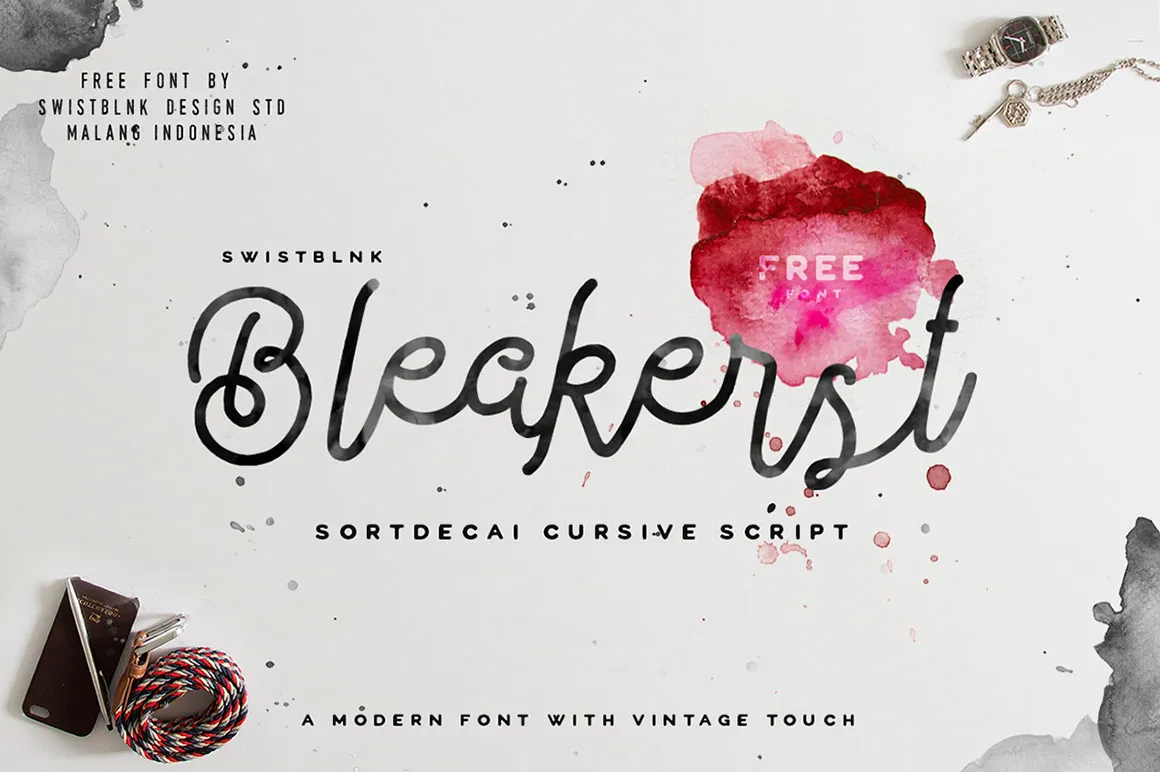
Bleakerst Script Font – Download Grátis
Esta fonte ‘Bleakerst Script Font’ é uma criação única e elegante que combina a modernidade com um toque vintage, ideal para novas identidades visuais. Desenvolvida por Agga Swist’blnk, essa tipografia cíliar tem um ar retro enquanto mantém os benefícios de uma fonte moderna, tornando-a perfeita para o design de logotipos. Inspirada no estilo dos typewriters antigos, ela traz um toque nostálgico que se encaixa perfeitamente em muitas aplicações gráficas, como logomarcas e materiais promocionais. Descubra sua versatilidade e faça o download hoje para começar a usar essa fonte moderna com um encanto vintage em seu próximo projeto. Enjoy!